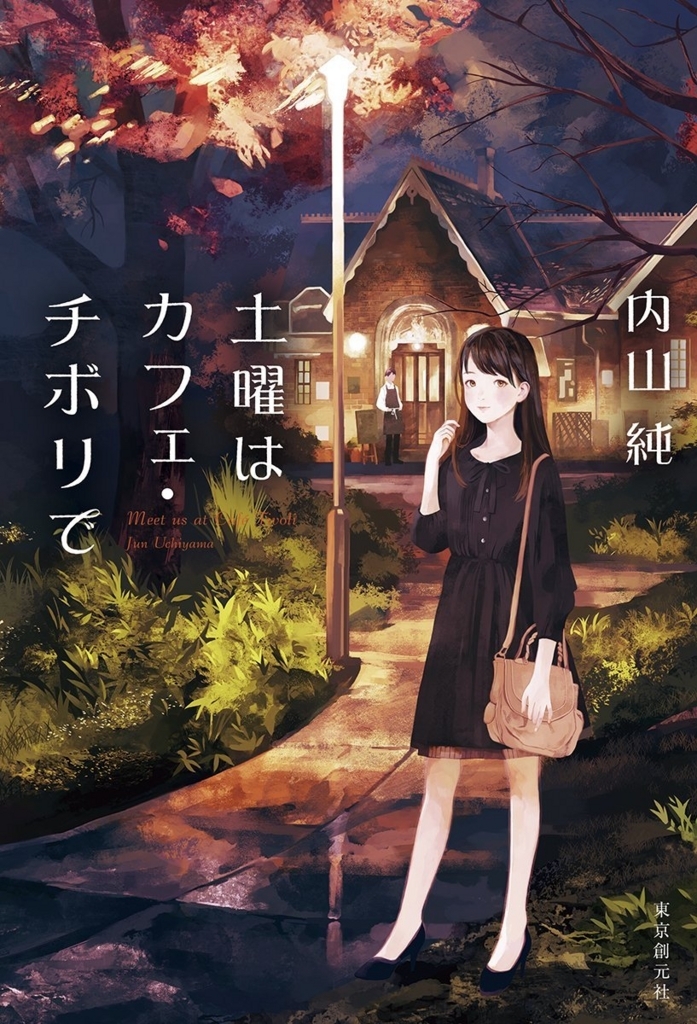
土曜はカフェ・チボリで
内山純氏著書による小説「土曜はカフェ・チボリで」は東京創元社から2016年5月29日に発売。
内山純Profile●1963年神奈川県生まれ。立教大学卒。2014年『Bハナブサへようこそ』で第24回鮎川哲也賞を受賞しデビュー。
土曜日のみの営業、さらにマスターは浮世離れした高校生という変わった喫茶店「チボリ」。けれど絶品のデンマーク料理と居心地の良い空間に、常連客はつい足が向く。おしゃべり好きのお客たちはいつのまにか各々の身に降りかかった不思議な事件のあらましを話し始めるのだった。それはアンデルセンの童話を彷彿とさせる出来事で……。風変わりな店主がふるまう美味しい料理と謎解きをどうぞご堪能ください。鮎川哲也賞受賞後第一作。
土曜はカフェ・チボリでのタイトルのフォントに麗雅宋が採用
ミステリー小説「土曜はカフェ・チボリで」のタイトルにダイナフォントの麗雅宋が一部加工されて採用されている。
麗雅宋
明朝体のストロークをより美しく、そして特徴的にアレンジし、華麗な雰囲気を演出したロマン風書体。タイトルやロゴ、キャッチコピー、TVのテロップやゲーム作品など幅広い用途で使用されている書体。麗雅宋の和文用仮名は「有限会社 字游工房」が制作している。